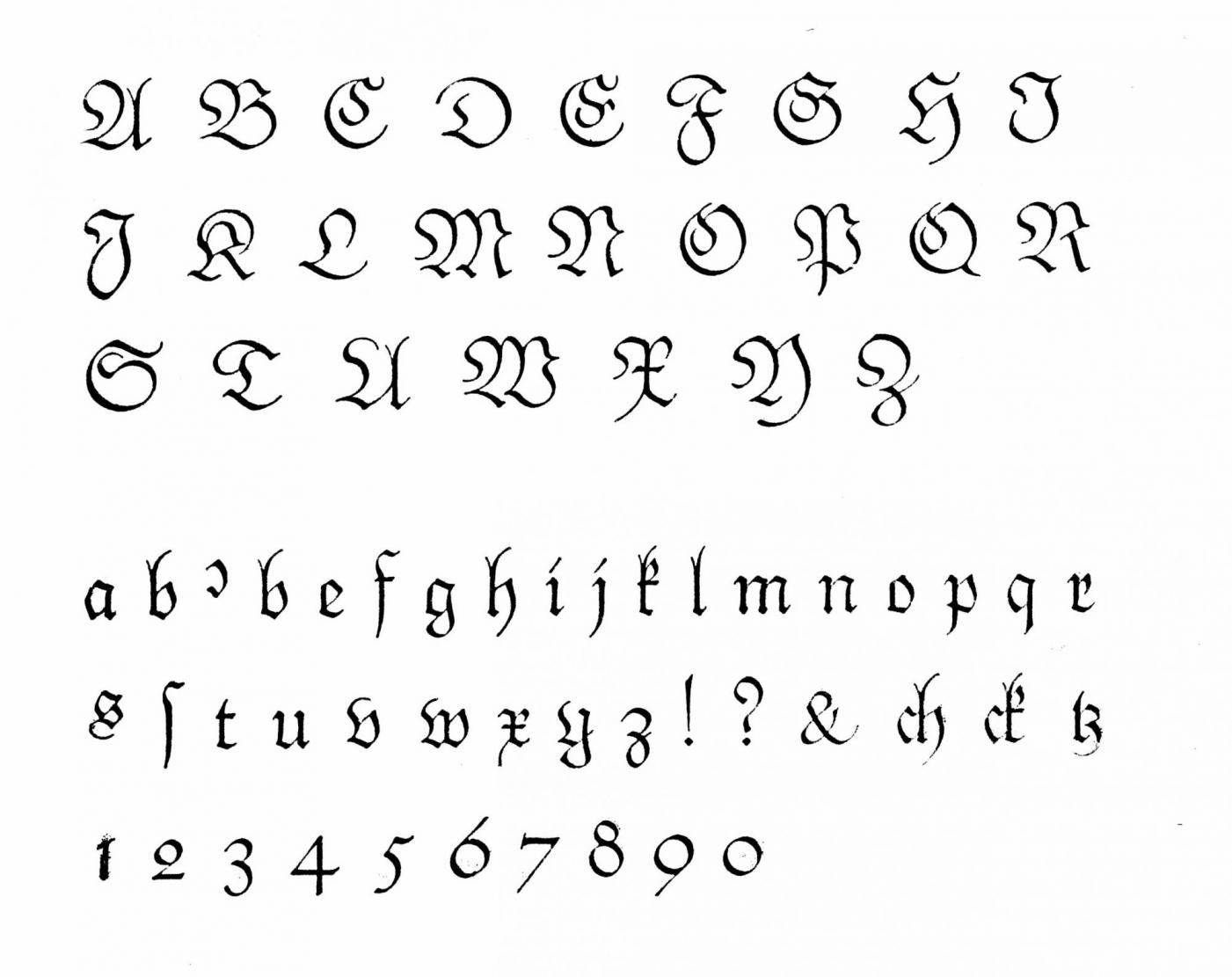
Setzkasten-Fraktur ohne Namen (Bleisatz)
wieder einmal bin ich auf der Suche nach dem Namen einer Bleisatz-Schrift aus einem Steckkasten.
Zumindest hab ich geschafft, mal ein "Schriftmusterblatt" zu setzen (ich weiss, Minuskel-c und -s sind verkehrtrum).
Ungewöhnlich finde ich die leichte Anmutung der Typen und die Ziffern – aber ich bin ja auch ziemlich unbeleckt, was Bleisatzschriften betrifft.
Leider gibt es von den Druckereien, die als Spender in Frage kommen, keinen mehr, der uns etwas zu Namen diverser Schriften sagen könnte.